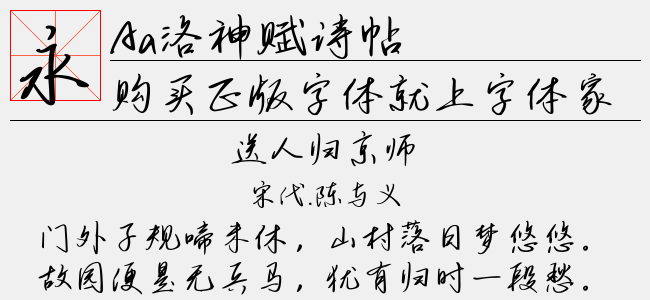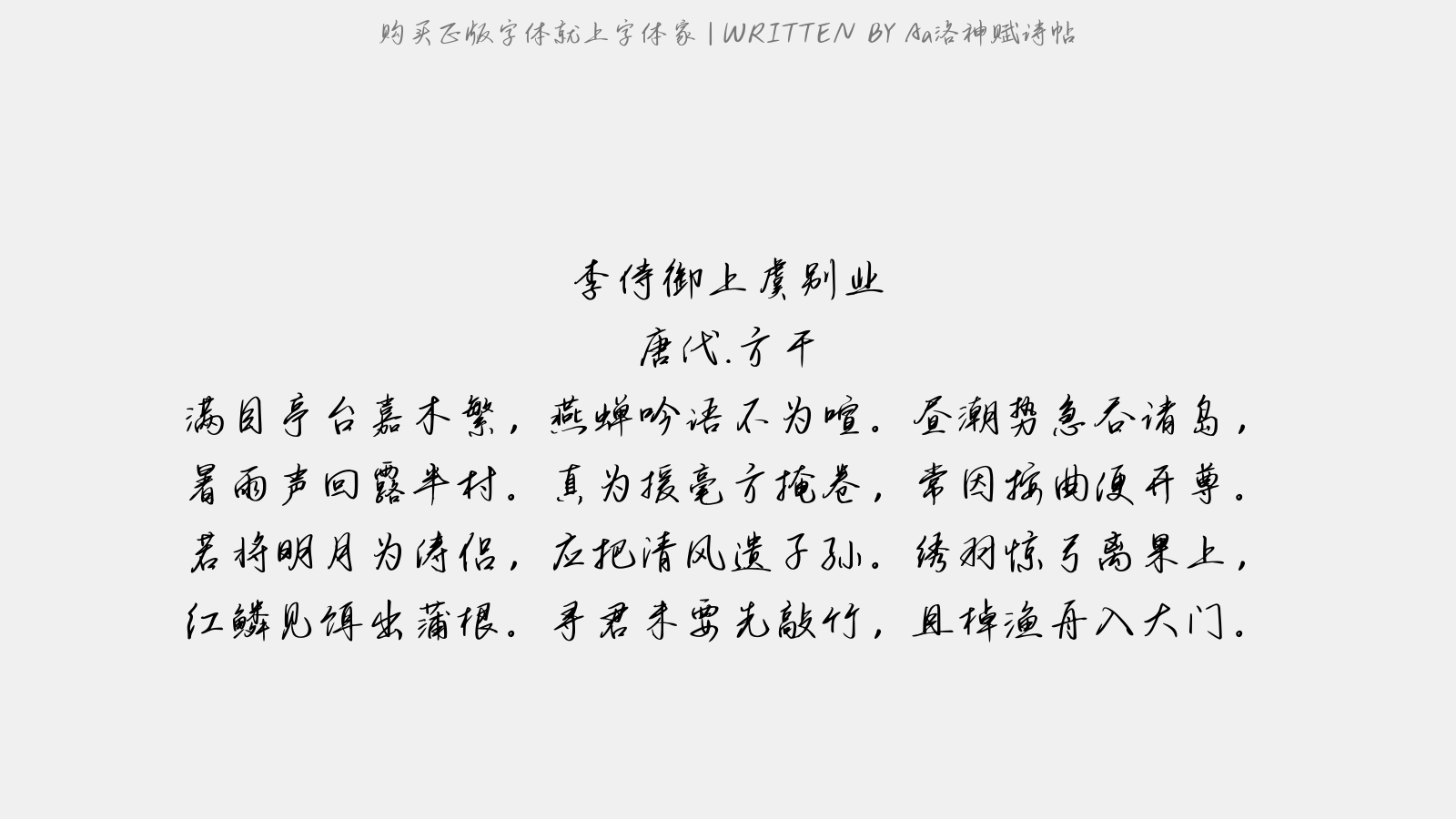
Aa洛神赋诗帖
字体作者:Aa字库
字体名称:Aa洛神赋诗帖
字体家族:Aa字库
书体类型:手写/印刷体
Aa洛神赋诗帖
Aa洛神赋诗帖是一款不错的艺术字体,由Aa字库出品,字体笔触适中,字形端正,具有很好的视觉感,适合应用于艺术设计、平面宣传设计、网页设计,书法字帖等领域,需要的朋友可以前来本站下载。